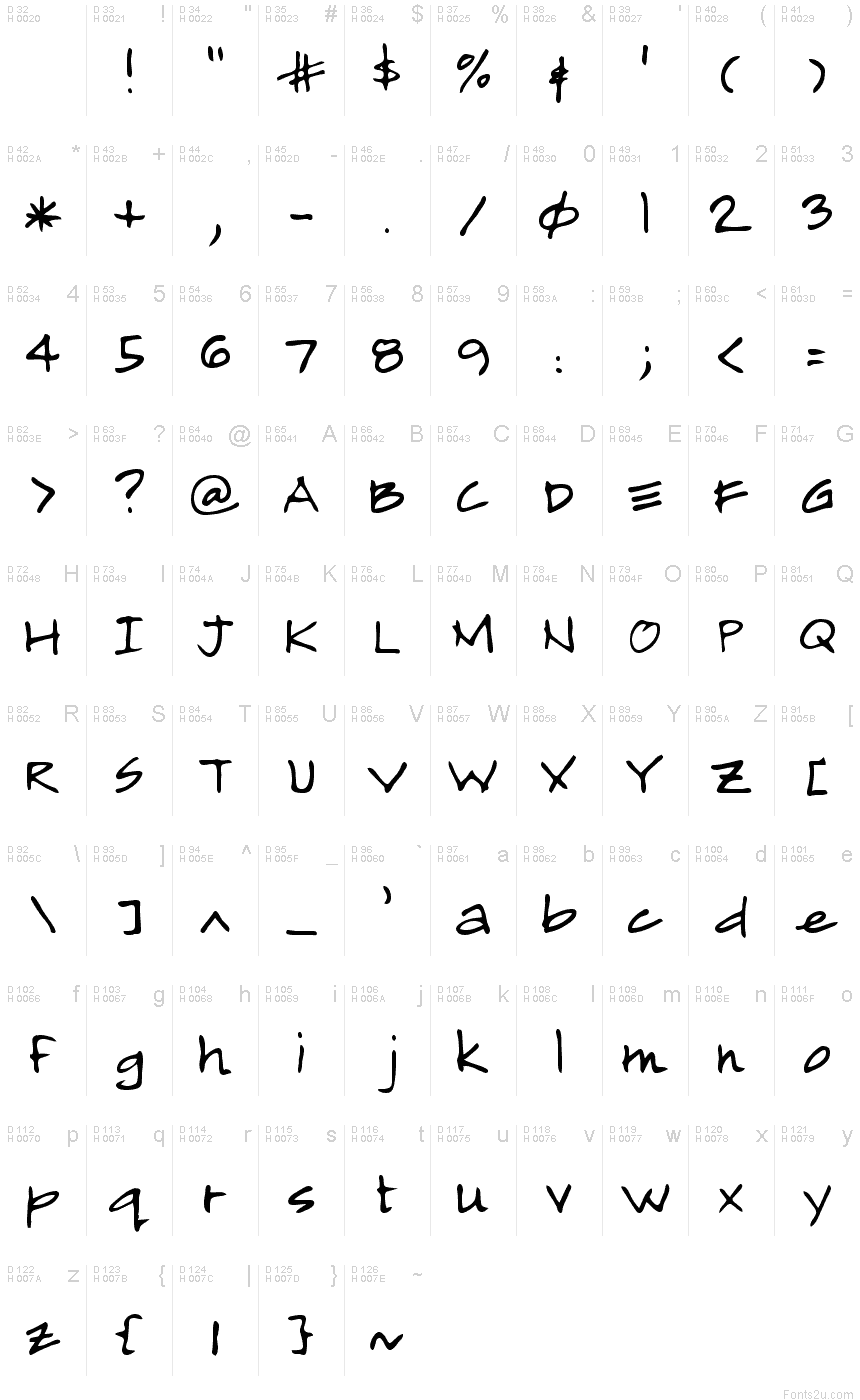
Almagro è un font script gratuito scritto a mano, con un ritmo audace e intenso che sembra tracciato direttamente col pennello sulla pagina. I tratti sono liberi e leggermente irregolari, con curve giocose e occasionali chiusure strette che gli conferiscono una personalità originale e umana, senza mai perdere di leggibilità. Ha lo spessore e il contrasto giusti per risaltare su sfondi complessi, mantenendo un aspetto informale e autentico.
Almagro brilla su copertine di libri, titoli di poster, grafiche per social media, biglietti d'auguri, packaging di prodotti e loghi con lettering a mano che richiedono carattere senza risultare troppo aggressivi. Il suo flusso vivace funziona magnificamente alle grandi dimensioni, dove la texture può davvero respirare. Per un abbinamento efficace, usa Almagro con un carattere sans serif geometrico e pulito per il testo principale, lasciando che il suo stile espressivo sia il vero protagonista.
Almagro